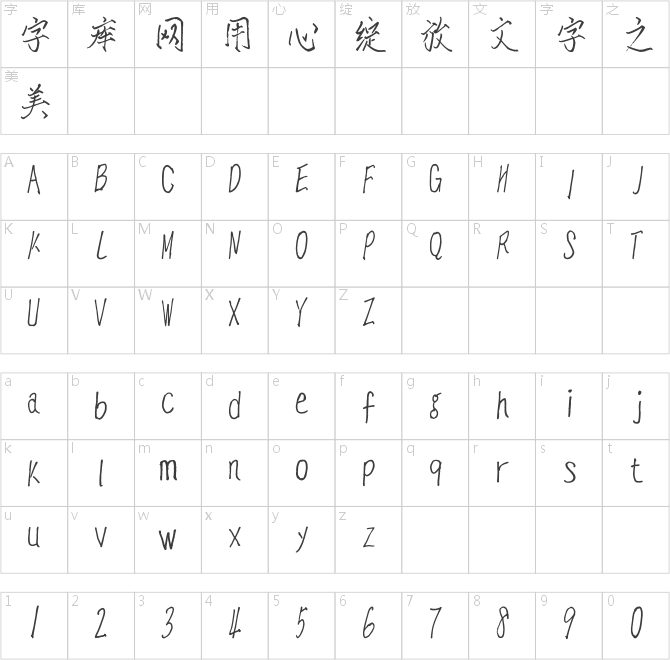
漢標(biāo)瘦金簡體
漢標(biāo)瘦金簡體字體瘦金字庫是一款讓人賞心悅目、百看不厭的中文字體,適合各類廣告和產(chǎn)品包裝設(shè)計應(yīng)用,字體大小3.91MB,格式為ttf字體,上傳用戶是漢標(biāo)文創(chuàng),作者/版權(quán)方為漢標(biāo)字庫